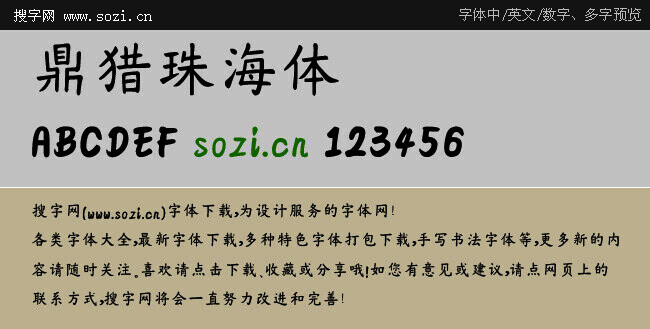
鼎猎珠海体
搜字网提供一款鼎猎珠海体中文艺术字体下载,鼎猎珠海体以珠海先贤苏曼殊墨宝,“金玉良言常佩带,芝兰浓馥振精神。”为缘起。是一套融入了珠海特质的字体。共计设计了7905个字符,其中汉字6916个。在6763个汉字基础上,特别增加了153个常用粤语汉字,可以满足绝大部分印刷设计等要求。这套字体面向全社会(包括企业商用)永久免费开放使用。但禁止用于任何违法违规用途。字体适合海报设计、广告创意、包装设计等应用。